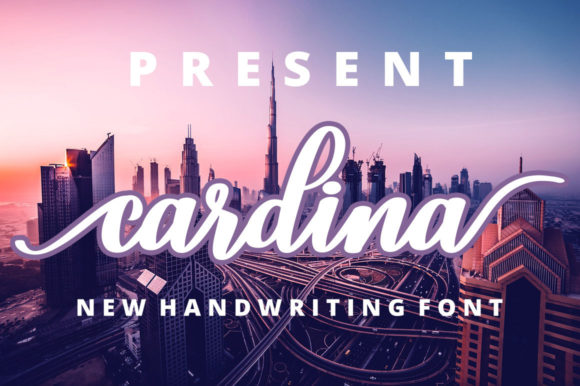
Cardina Font
Cardina Font – لمسة أنيقة لتصاميمك الإبداعية
أضف لمسة من الفخامة والتميز إلى أعمالك مع خط Cardina، الخط العصري الذي يجمع بين الأناقة والبساطة في آنٍ واحد. يتميز هذا الخط بانسيابيته وتفاصيله الدقيقة، مما يجعله مثاليًا لتصميم الشعارات، والعلامات التجارية، والدعوات، والمطبوعات، والمحتوى الرقمي.
✔ متعدد الاستخدامات – مثالي للمشاريع الفاخرة والتصاميم العصرية.
✔ جودة عالية – خطوط واضحة ومتقنة تناسب مختلف الاستخدامات.